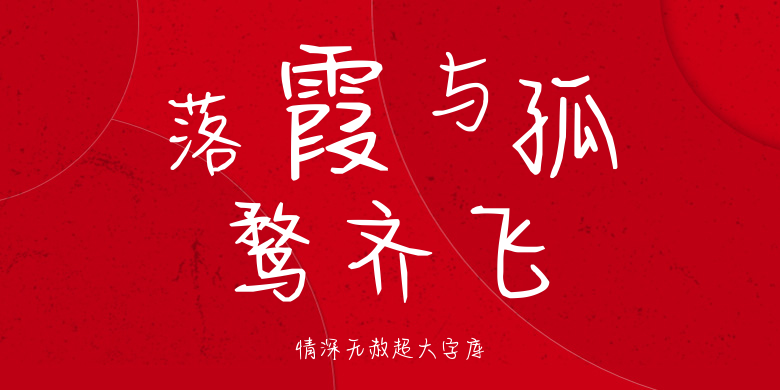
情深无赦超大字库
情深无赦超大字库,这款字体结构工整、笔画清晰,兼顾美观与易读性,适用于标题、正文、海报、包装、LOGO 等多种场景。字形优雅稳定,风格百搭耐看,适配日常排版与创意设计,让文字呈现更舒适、更具质感。情深无赦超大字库一笔一画,皆是细节,以均衡的比例、流畅的线条打造舒适视觉体验,字形端正大气,风格简约现代。无论是商业设计、品牌宣传还是日常排版,都能轻松驾驭,让文字更有格调与力量。情深无赦超大字库字体下载。